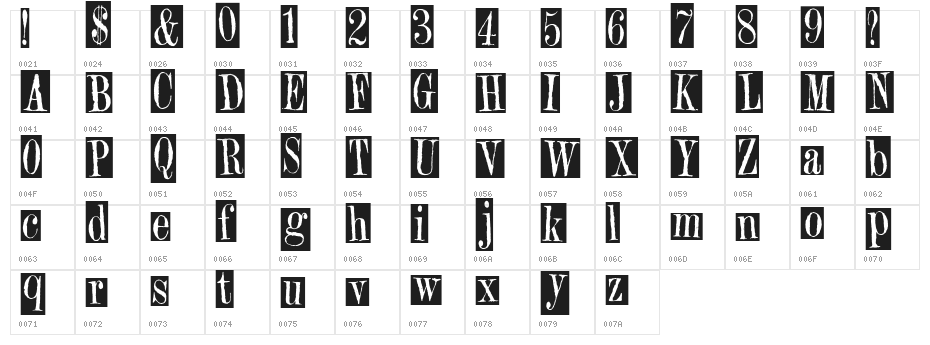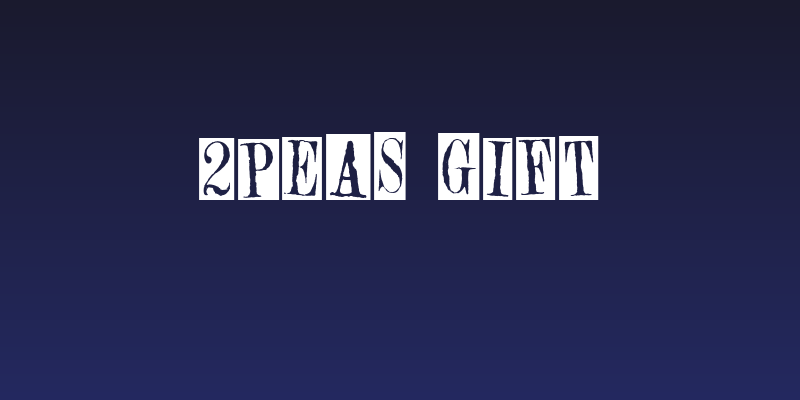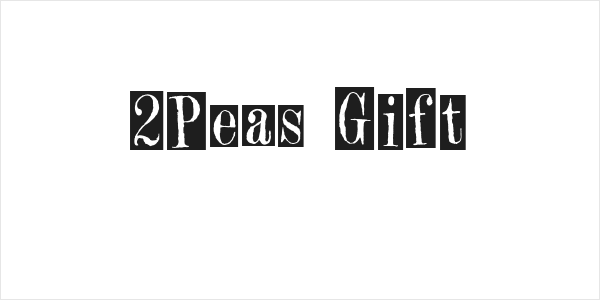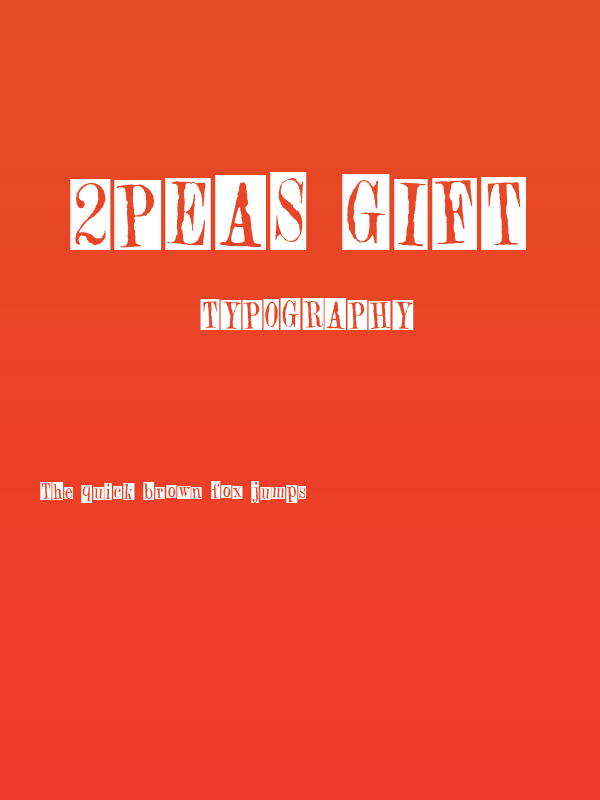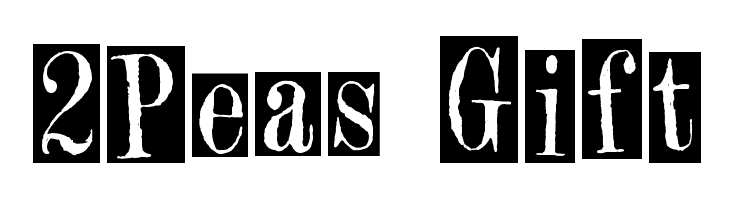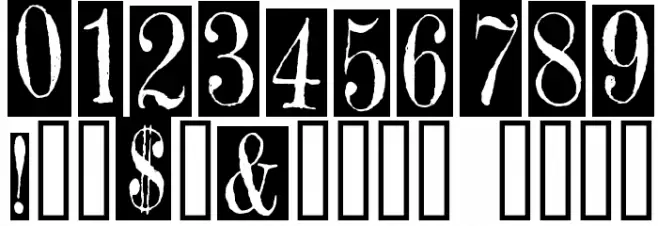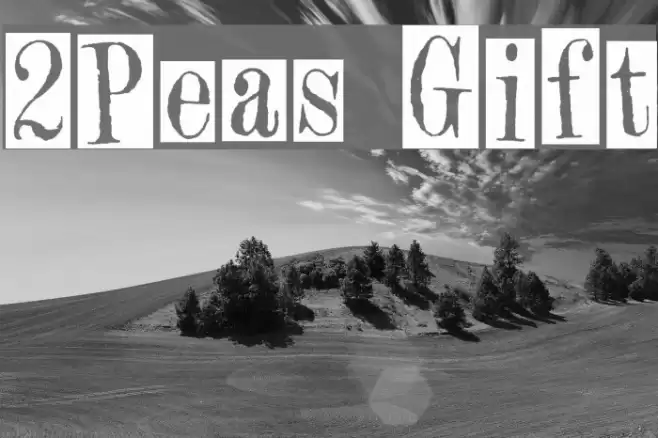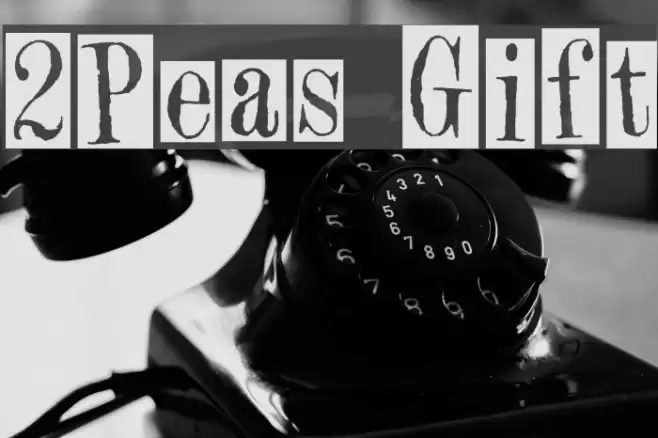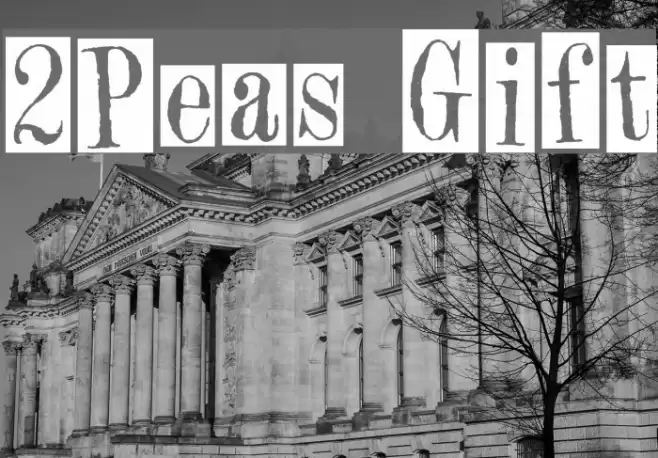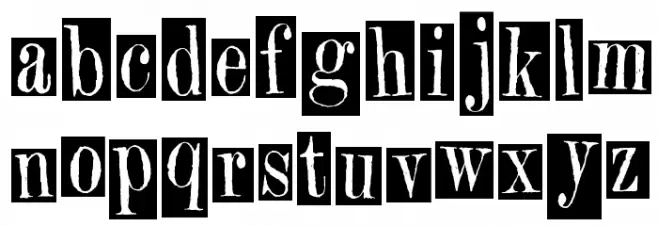
2Peas Gift Font
| Gesamtstil | Whimsical, Artistic |
| Anwendungsfall | Headlines, Creative projects |
| Vorgeschlagene Projekte | Ideal for greeting cards, scrapbooking, children's books, and creative posters. |